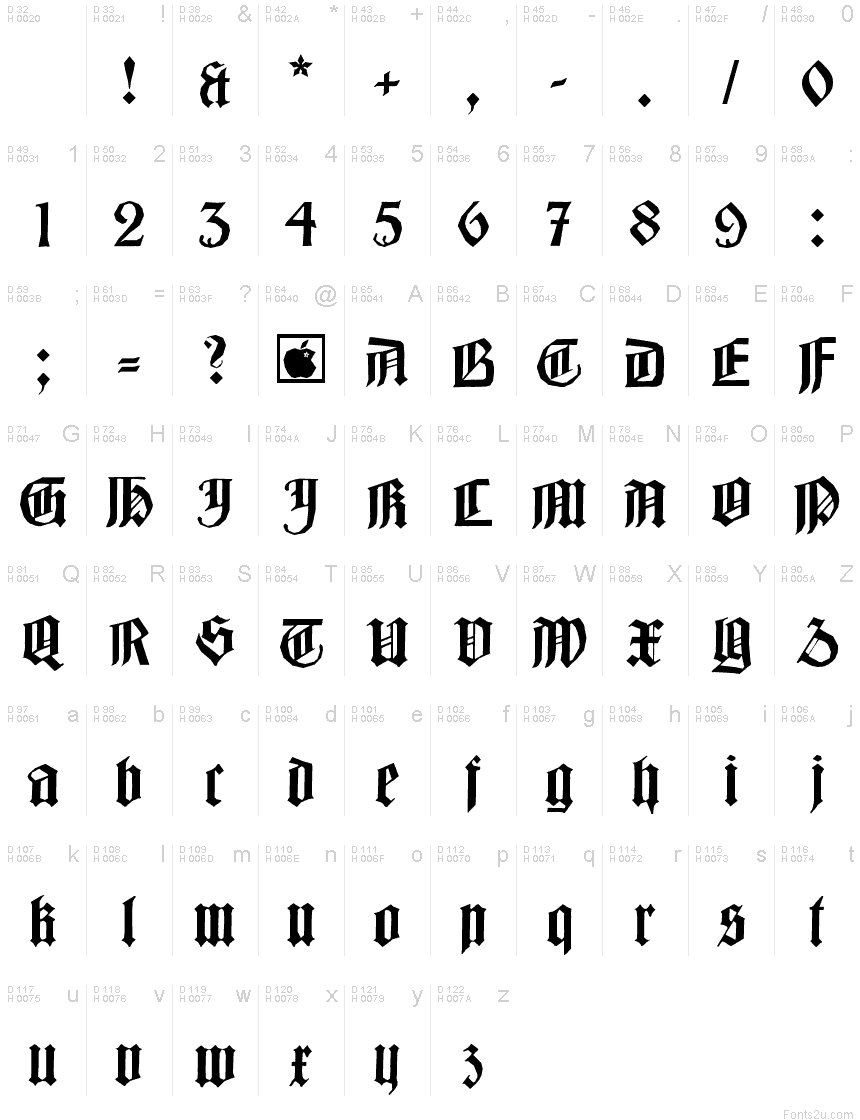
Barlosius Edged autorstwa M. Klein to darmowy, kanciasty font typu blackletter o wyrazistym, średniowieczno-gotyckim charakterze. Litery sprawiają wrażenie wyciosanych, a nie narysowanych – mają ostre kąty, fasetowane krzywizny i zwarte, pionowe formy, które nadają krojowi surowy, monumentalny wygląd.
Świetnie sprawdzi się na plakatach, okładkach książek, etykietach browarów, grafikach festiwalowych czy merchu zespołów, wszędzie tam, gdzie historyczny klimat potrzebuje „pazura”, a nie zbędnych ozdobników. Jako darmowy font, idealnie nadaje się też do krótkich nagłówków, plansz tytułowych i monogramów, ponieważ ostre cięcia i wyraziste sylwetki liter zachowują swój charakter nawet w najkrótszych słowach.